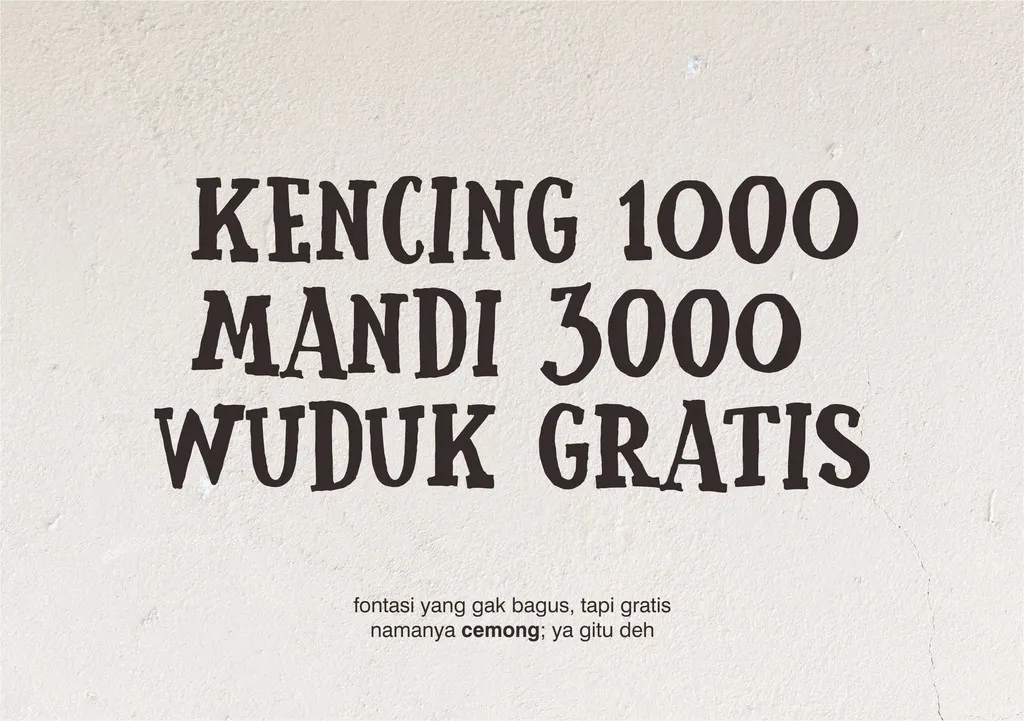
A fonte Cemong é uma escolha perfeita para quem busca uma fonte typewriter vintage, especialmente adequada para escrever preços na entrada de supermercados, num ambiente menos sofisticado como bairros urbanos e terminais de ônibus. Suas linhas sóbrias e robustas dão um toque realista ao texto, que se destaca perfeitamente em ambientes mais simples ou onde há uma necessidade de manter a leitura fácil e clara. Desenvolvida pelo designer Gunarta, Cemong traz um touch de nostalgia com sua tipografia minimalista, sem perder o respeito pelos detalhes essenciais para garantir que os preços sejam legíveis sob qualquer condição. Esta fonte typewriter é ideal tanto para uso pessoal quanto para pequenas empresas em áreas menos urbanizadas, oferecendo uma solução prática e elegante para um elemento tão básico da experiência de compra.